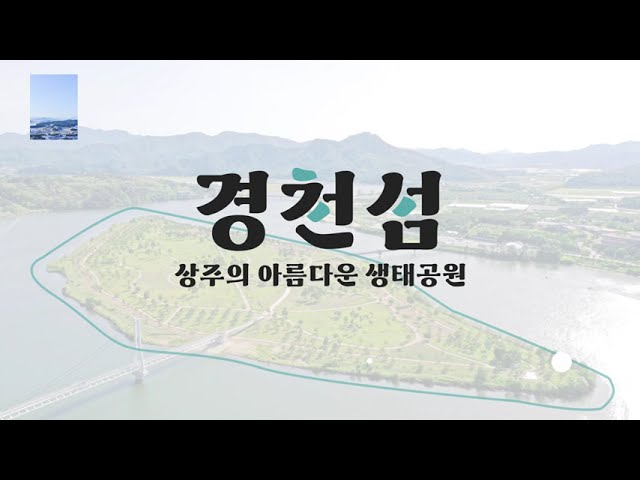
상주경천섬체
상주의 대표 관광지인 경천섬을 모티브로 제작된 서체입니다. 섬의 이미지를 형상화하여 분리된 내리점을 갖습니다.
상주경천섬체
상주의 대표 관광지인 경천섬을 모티브로 제작된 서체입니다. 섬의 이미지를 형상화하여 분리된 내리점을 갖습니다.
상주 대표 관광지인 경천섬을 모티브로 제작한 서체입니다.
내리점을 분리하여 섬의 이미지를 형상화하였습니다.